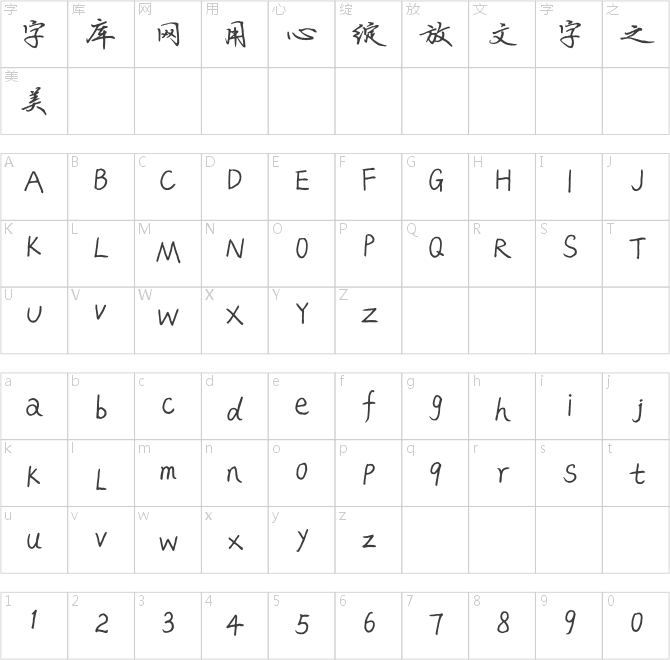
字体名称: 云峰寒蝉体
云峰寒蝉体
云峰寒蝉体介绍
云峰寒蝉体,一款可应用于多场景的手写字库,字体大方美观,笔锋力道,云峰字库专注于字库开发设计,字库交流QQ群:205961668
云峰寒蝉体字体字库是一款让人赏心悦目、百看不厌的中文字体,适合各类广告和产品包装设计应用,字体大小4.37MB,格式为ttf字体,上传用户是梦逍遥,作者/版权方为云峰字库